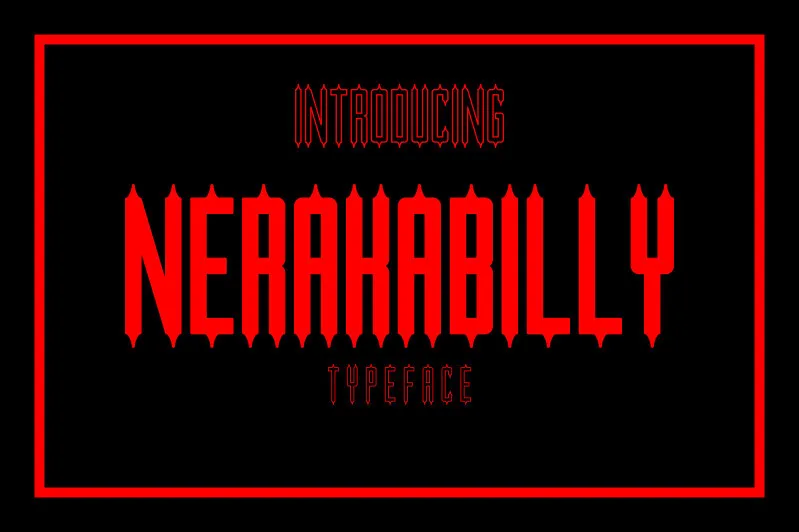
Nerakabilly Typeface – Fonte Grátis
Nerakabilly Typeface
Esta fonte “Nerakabilly Typeface” é perfeitamente adequada para adicionar um toque único a qualquer projeto decorativo ou artístico. Seu design icônico e vibrante combina detalhes elaborados com uma sensibilidade minimalista, o que o torna ideal tanto para criações comerciais quanto pessoais. Com uma abordagem rica em contrastes de cores e linhas elaboradas, “Nerakabilly Typeface” oferece a oportunidade de explorar sua criatividade ao criar cartazes publicitários, revistas ilustradas ou até mesmo gráficos para redes sociais. O designer daxdu28 trouxe vida a cada caractere da fonte, garantindo que o seu uso não seja apenas um ato estético, mas uma forma de expressão. Com certeza, qualquer aplicação comercial desta fonte será gratificada por ela, e até mesmo um simples donativo é muito apreciado. Seja por seus detalhes exuberantes ou sua simplicidade elegante, a “Nerakabilly Typeface” é uma escolha inteligente para quem busca uma fonte que pode expressar tanto seu poder visual quanto seu estilo pessoal.